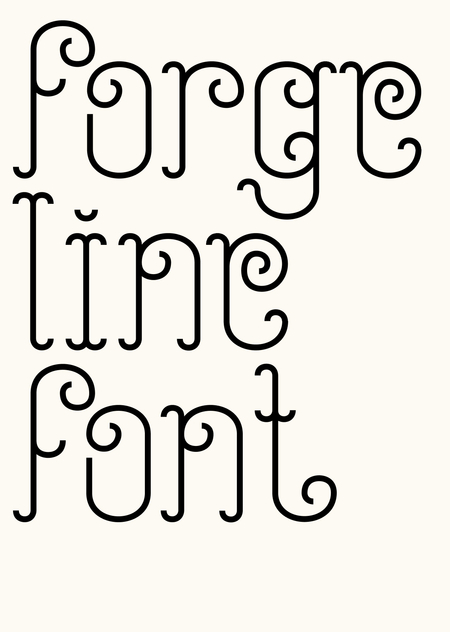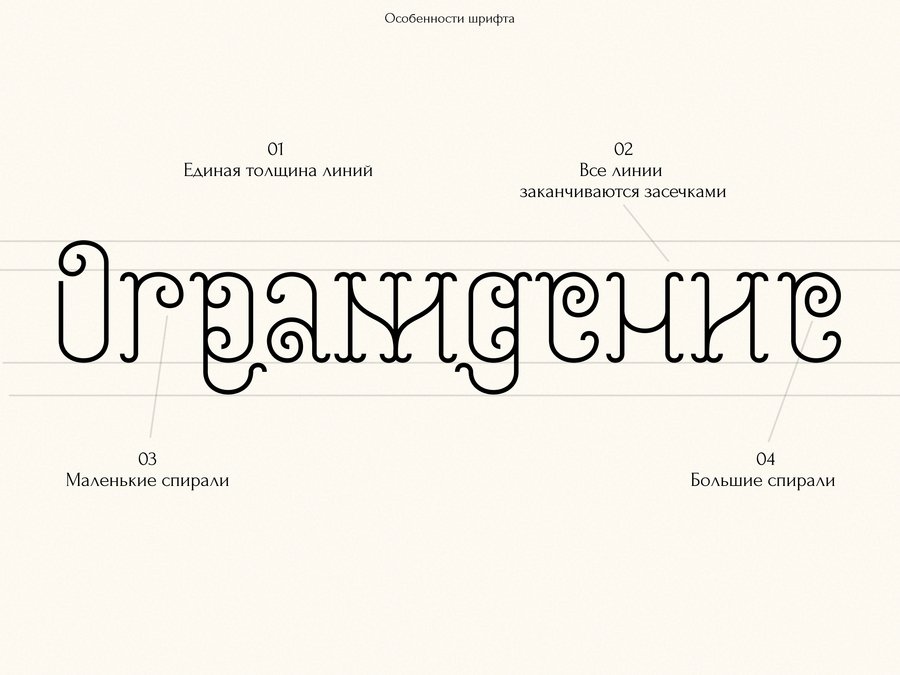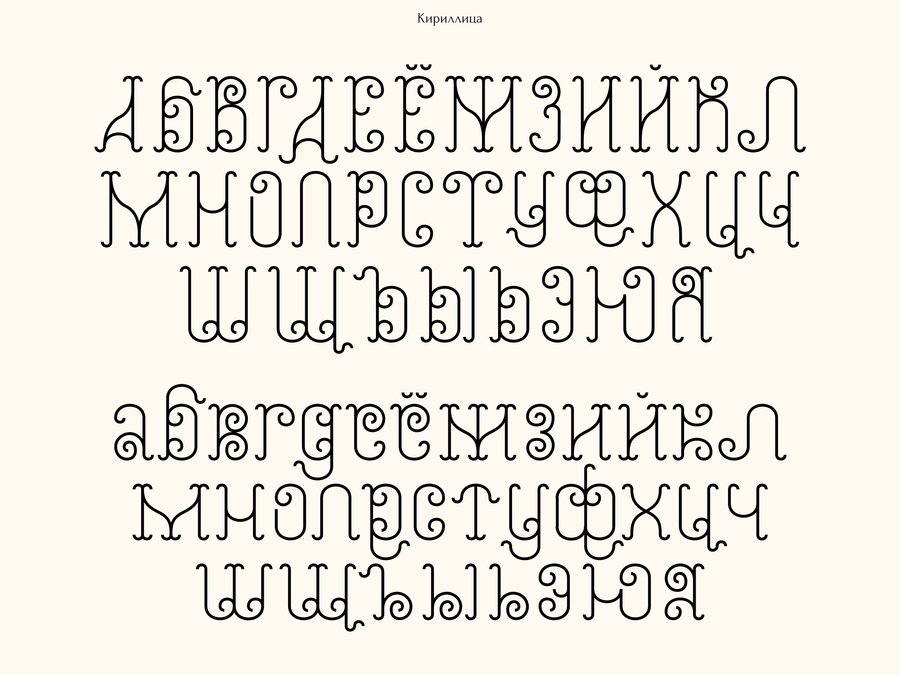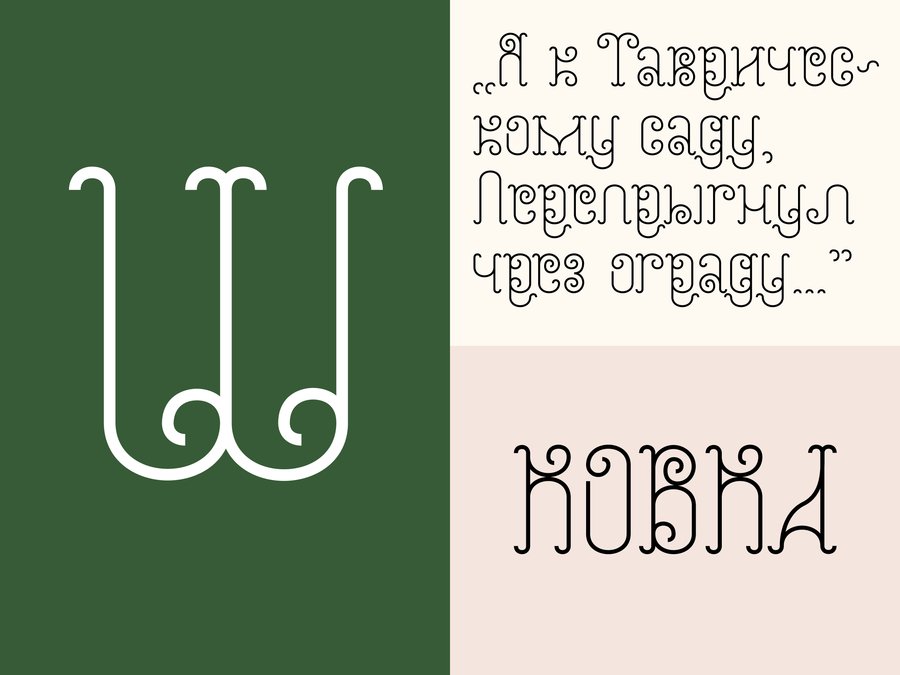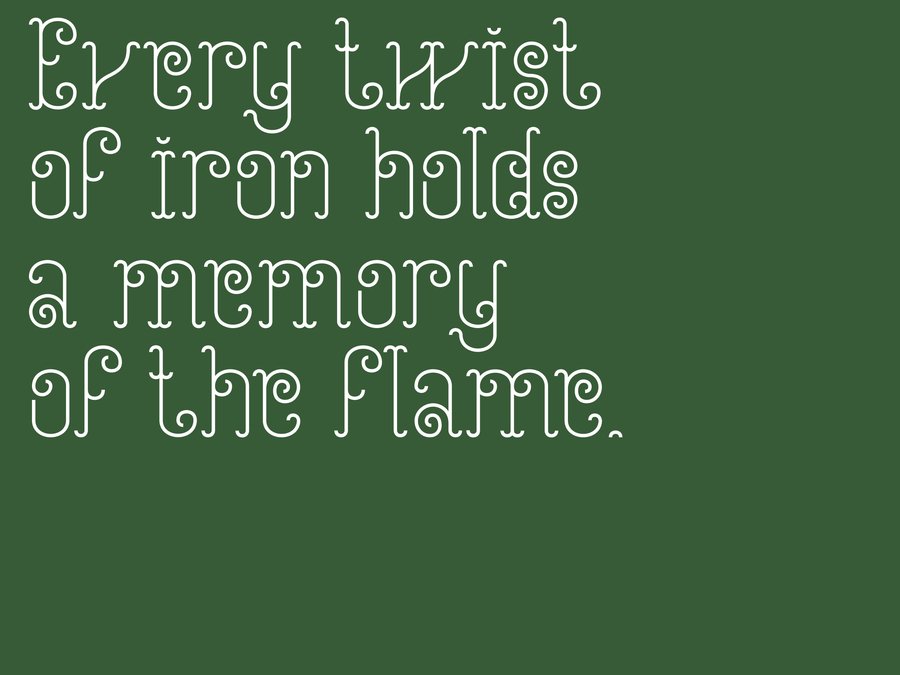
Forgeline font — шрифт, вдохновленный художественной ковкой и ограждениями
Буквы единой толщины выстроены как элементы кованой конструкции, где вертикали прямые, подобные столбам ограды, а горизонтали и пересечения похожи на ажурные завитки